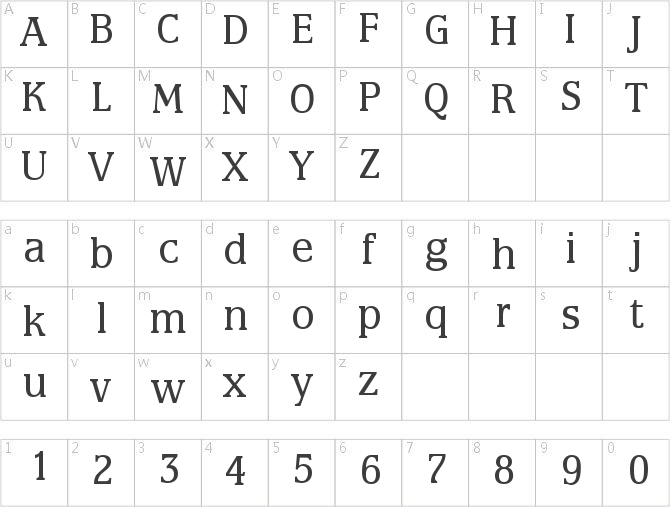
MarlonBookDB-Normal 詳情頁
MarlonBookDB-Normal字體字庫是一款讓人賞心悅目、百看不厭的英文字體,適合各類廣告和產(chǎn)品包裝設(shè)計(jì)應(yīng)用,字體大小0.05MB,格式為ttf字體,上傳用戶是一直在守護(hù),作者/版權(quán)方為未知